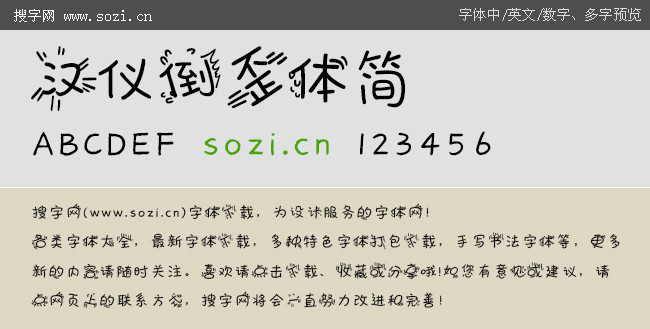
漢儀倒歪體簡(jiǎn)
搜字網(wǎng)給大家提供一款漢儀倒歪體簡(jiǎn)中文字體下載,漢儀倒歪體簡(jiǎn)字體是一款非常有特色的卡通字體文件。字體倒歪著,字體筆畫設(shè)計(jì)添加了符號(hào),顯得非?蓯(ài)。適用于兒童畫冊(cè)設(shè)計(jì)、卡通海報(bào)設(shè)計(jì)、包裝設(shè)計(jì)等場(chǎng)合使用。(本字體為個(gè)人非商用版,如需要商用請(qǐng)聯(lián)系漢儀公司購(gòu)買版權(quán))